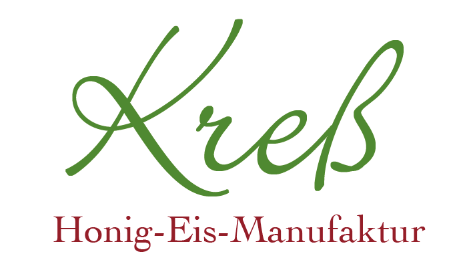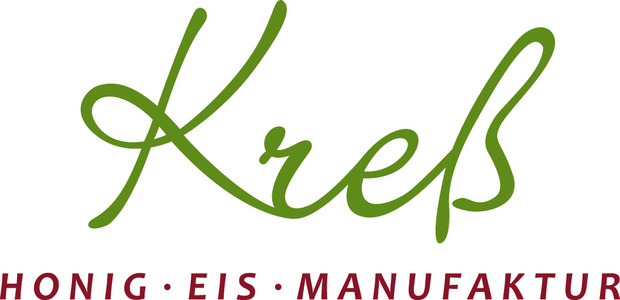
Welche Schrift würde zu diesem Logo (Schrift) passen
Ich habe ein Logo (mein Name)
Ich suche eine Schrift die edel (edles Produkt ein Honigeis) und unverwechselbar ist (weiß nicht ob es so was gibt)
Entschuldige, dass ich antworte ohne einen Schriftvorschlag … aaaber:
Die Verbindung zwischen K und r in Kreß ist irgendwie seltsam. Soll zwar handgeschrieben aussehen, aber wer schreibt denn Kr so? Wirkt auf mich seltsam …
Außerdem lese ich in der unteren Zeile: „Honig“ [pause] „Eis“ [pause] „Manufaktur“ verstehe das ganze also als Aufzählung, man könnte in diesem Sinne auch Honig, Eis und Manufaktur schreiben.
Diese Darstellung macht für mich mehr Sinn, wenn es drei Produkte gibt, bspw. Honig ‧ Marmelade ‧Nutella oder so … Wenn es ein Begriff sein soll – und das vermute ich stark – dann sollte man hier die Rechtschreibungsregeln nicht brechen und mit schnöden Bindestrichen verbinden, also: Honig-Eis-Manufaktur. Und es sei nur erwähnt, dass hier im Forum der ein oder andere eine Allergie gegen Bindestriche hat und Honigeismanufaktur läse. Ich finde diese Variante auch schöner.
Dem schließe ich mich an und werfe mal die Champion Script in die Runde ... oder auch die Bodoni Script aus dem gleichen Hause.
Wen’s richtig edel und einzigartig werden solle empfehle ich ein individuelles Handlettering.
Das mit den Bindestichen ist im Logo nicht drinne da sind Punke.
Das r ist halt so geworden damit muss ich leben.
Es sind drei Produkte Honig, Eis (Honigeis), Manufaktur
Das r ist halt so geworden damit muss ich leben.
Mußt Du nicht. Das wäre der wichtigste Punkt, wo man ansetzen sollte, wenn man das Erscheinungsbild verbessern will.
Es sind drei Produkte Honig, Eis (Honigeis), Manufaktur
Das verstehe ich nicht. Ich denke, es ist eine Manufaktur, die Honigeis produziert? Die Manufaktur selbst ist doch kein Produkt, oder?
Ah, sorry, ich hatte das, glaube ich, falsch verstanden. Ich dachte die Schrift im Logo soll ersetzt werden :oops:
Welche Schrift ist das in der Unterzeile? Ich würde ja einfach die weiter verwenden und nicht noch eine dritte dazu suchen ...
Außerdem sollte man m. E. nicht mit einem Logo leben müssen, das muss schon wie angegossen passen. Ich sag’ ja auch nicht:»Och, ich habe nur so olle abgeschrabbelte, schlecht sitzende Jeans, das ist schon okay, wenn ich damit zum Kundengespräch gehe.« :neenee:
Das mit den Bindestichen ist im Logo nicht drinne da sind Punke.
Ja, das sieht man. Aber auch ich verstehe immer noch nicht, warum da Punkte sind. Ich lese das so, als ob da stünde: Hier gibt es Honig, hier gibt es Eis und hier gibt es eine Manufaktur. Das mag ja richtig sein, aber dann könnte man genauso gut noch dazu schreiben: Hier gibt es eine Eismaschine. Hier gibt es Milch. Hier gibt es Löffel. Hier gibt es Zucker. Hier gibt es ...
Das r ist halt so geworden damit muss ich leben.
Gut, dass es dann wenigstens grün geworden ist und nicht lila.
Es sind drei Produkte Honig, Eis (Honigeis), Manufaktur
Ah, jetzt verstehe ich: Hier werden drei Produkte hergestellt (oder vielleicht auch: hier kann man drei Produkte kaufen), nämlich Honig, Honigeis und außerdem auch eine Manufaktur. Ein sehr interessanter Laden, so etwas ist mir noch nicht begegnet.
Hallo Honigeis,
mit dieser Art Antworten hast du wahrscheinlich nicht gerechnet, aber wenn man die Experten fragt, muss man natürlich auch mit den Expertenantworten leben. ;-) Ich stimme meinen Vorrednern zu: Das Logo geht so nicht! Der Designer wusste nicht, was er tat. Hast du eine Vektordatei davon (EPS, PDF etc.)?
Dann nimm die, suche dir einen neuen Designer deines Vertrauen und lasse das Logo optimieren. Das geht sogar ohne viel Aufsehen und ohne dass man es ein »neues Logo« nennen muss. Einfach kleine Korrekturen: Das K und r müssen korrekt verbunden werden. Und die Unterzeile muss Honigeis-Manufaktur (besser) oder gegebenenfalls Honig-Eis-Manufaktur (auch okay) geschrieben werden. Die jetztige Schreibung ist totaler Unsinn.
Bei der Schriftwahl für Deine Drucksachen würde ich einfach bei den ohnehin im Logo benutzen Schriften bleiben. Das sind nun schon zwei Stile. Da noch eine dritte Schrift hinzuzunehmen, macht die Sache nicht unbedingt besser, egal ob Freeware oder kommerziell.
Nur schnell hingeschmiert … ich würde in diesem Fall die Bickley Script so lassen wie sie daherkommt, bis auf das "ß", und eine Schrift wählen, die wenigstens irgendwie nach Handgemachtem, Wertvollem aussieht.
Sinnvoll fände ich dann allerdings statt nur dem Logo gleich ein Komplettpaket, auch für die Honigglasetiketten etc. Ich hab auf deiner Seite keine Bilder von Produkten gefunden (vielleicht sind sie auch nur gut versteckt), deswegen weiß ich nicht, wie die verpackt sein können (außer vermutlich der Honig in den typischen Gläsern).
PS: Heißt es „Kreß“ oder „Kress“? Das ist auf deiner Seite mal so und mal so geschrieben.